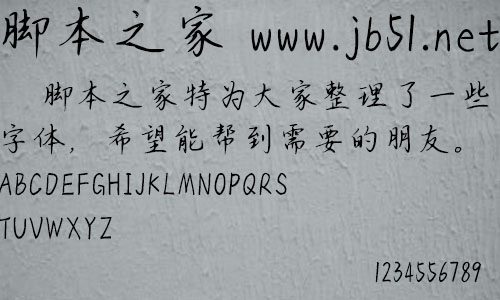
漢儀雨天時(shí)愛雨簡(jiǎn)一款不錯(cuò)的藝術(shù)字體,由漢儀字庫出品,字體筆觸纖細(xì),書寫流暢,具有很好的視覺感,適合應(yīng)用于藝術(shù)設(shè)計(jì)、平面宣傳設(shè)計(jì)、網(wǎng)頁設(shè)計(jì),書法字帖等領(lǐng)域,需要的朋友可以前來本站下載。